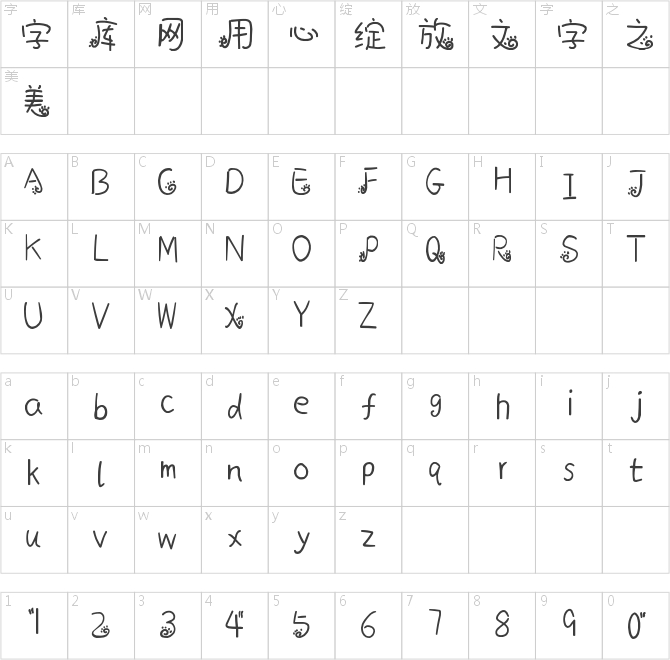
七月夏日炎炎 详情页
字体名称: 七月夏日炎炎
作者版权: 方正手迹
七月夏日炎炎
七月夏日炎炎介绍
七月夏日炎炎这是一款简笔画风格手绘字体,作者大量使用简笔画风格的流汗、太阳等元素,替换或装饰衔接上一些部件,搭配独特的字形,生动展现出七月夏日炎炎的景象。适用于少儿类的书刊、品牌广告和产品包装设计,综艺漫画用字,以及社交网络的个性化用字。